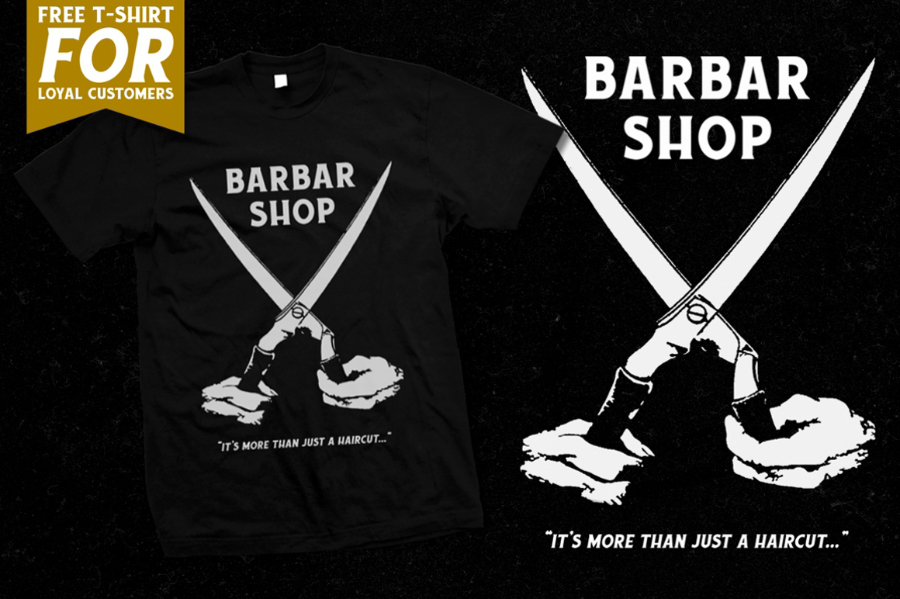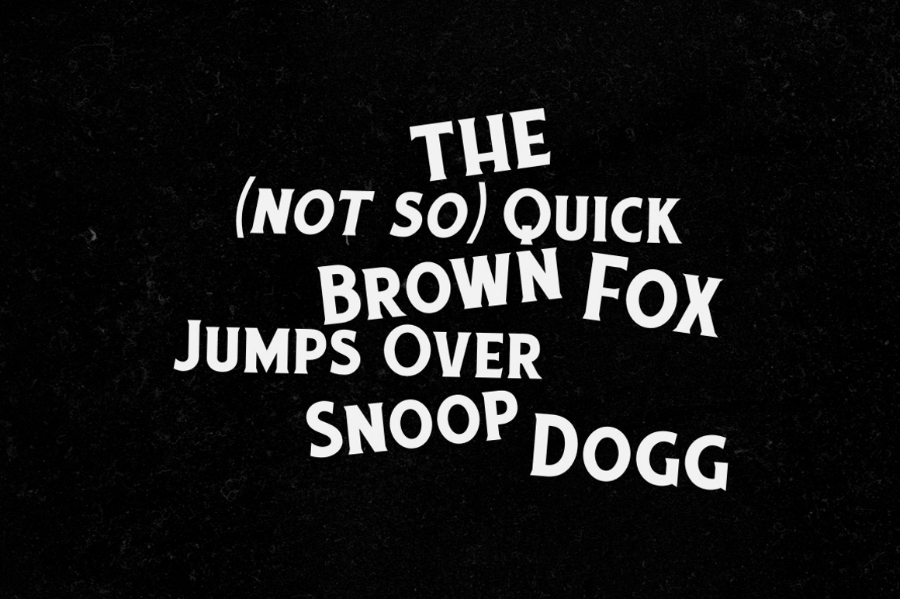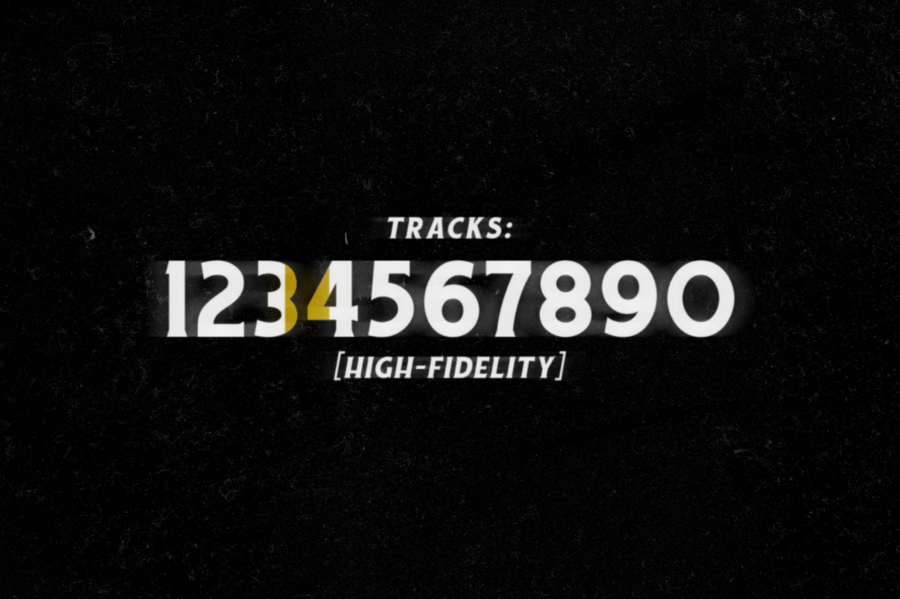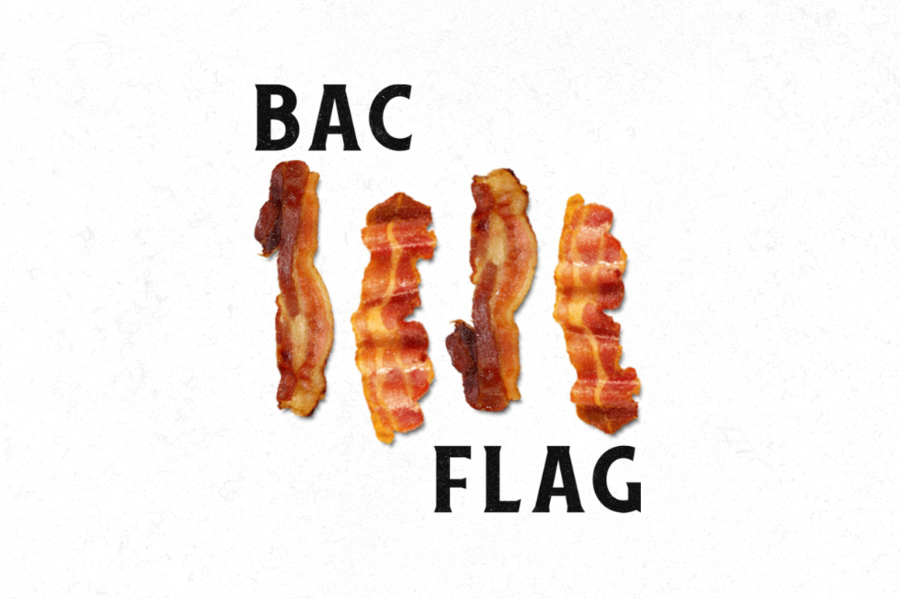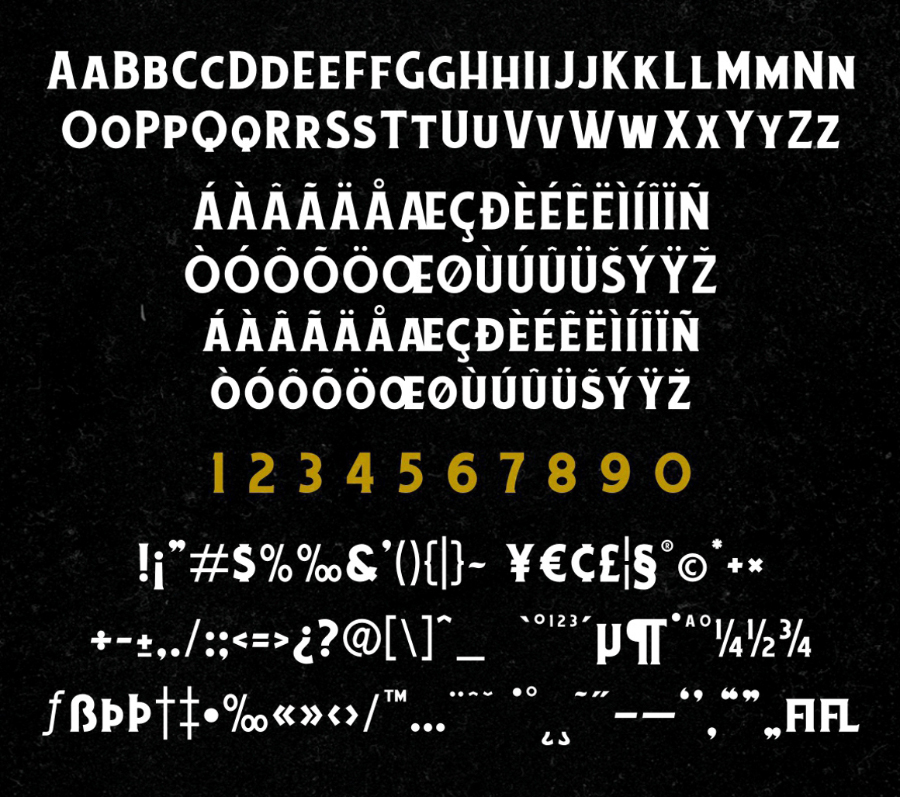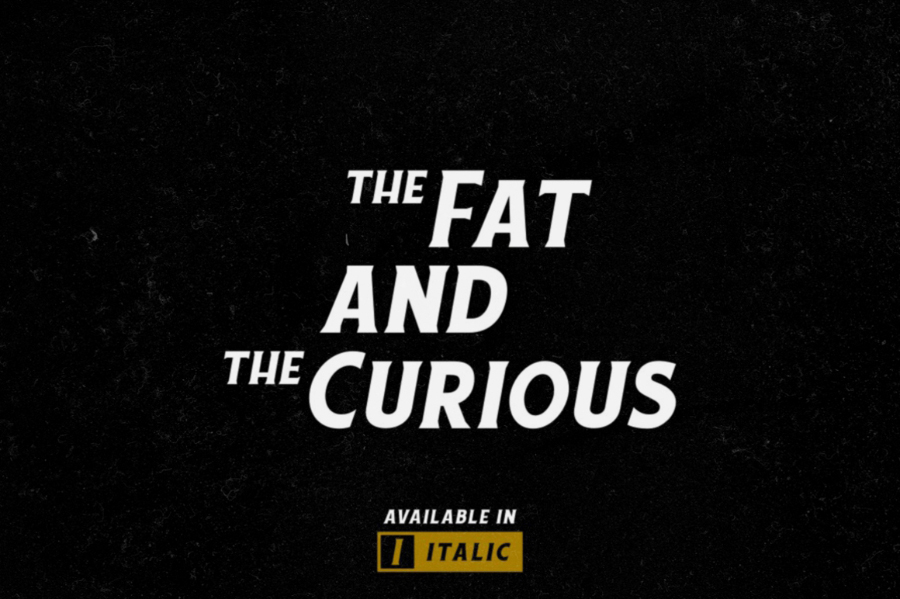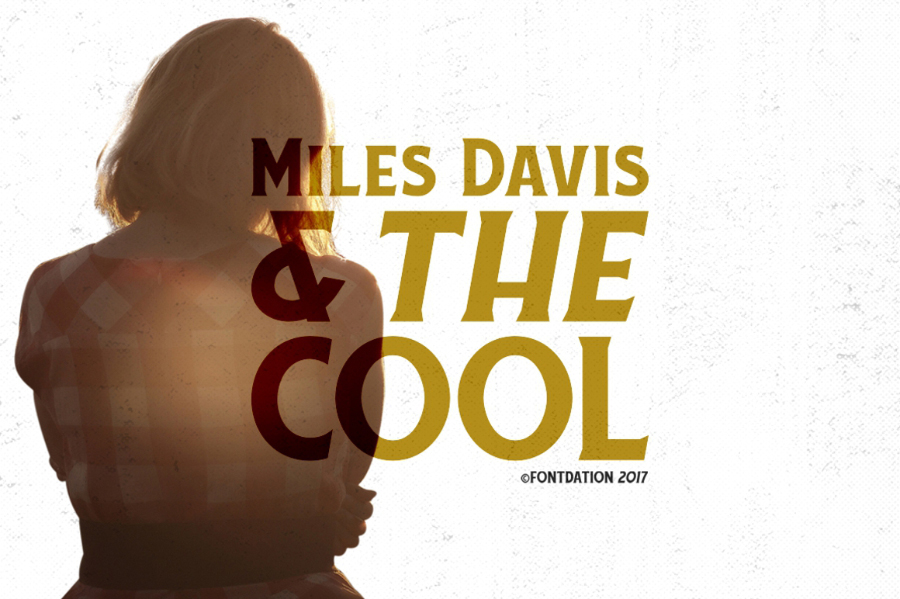
Chuck Noon 2免费字体
查克中午2免费字体是从其前任重画和重新排版的版本。一些在这里和那里调整,添加了一些多语言字符,当然,还有斜体版本!这种看起来很难看的字体最适合任何场合,您可以将它们用于您的所有设计项目。好消息是,这个字体是免费的个人和商业使用!你还在等什么?去下载和(AB)使用EM!